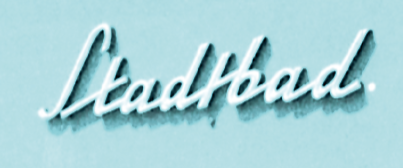
50er Jahre Schrift: Ich suche für eine denkmalgeschütze Kundenimmobilie die Originalschrift aus ca. 1965. Wer könnte mir da weiterhelfen? Vielen Dank schonmal.